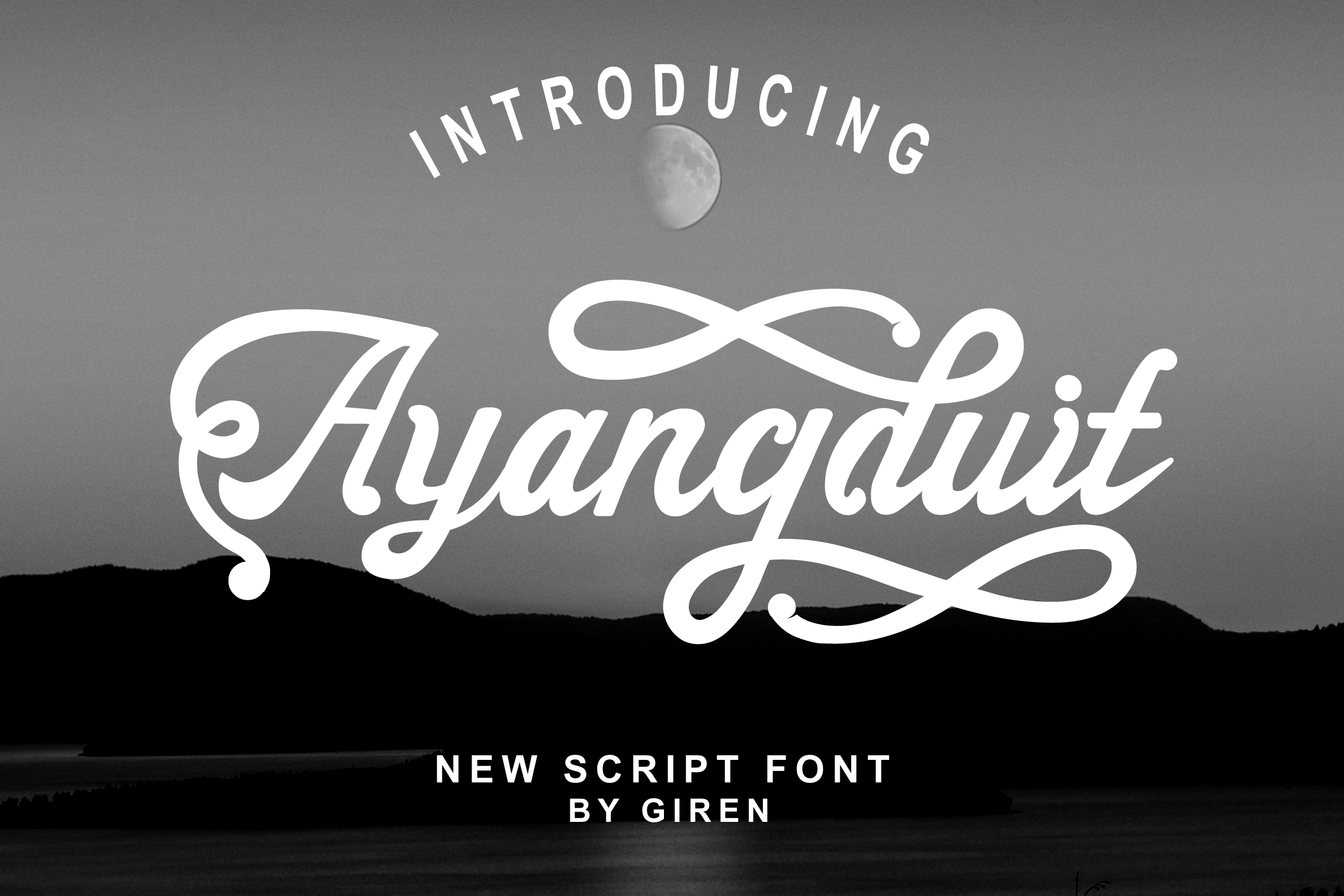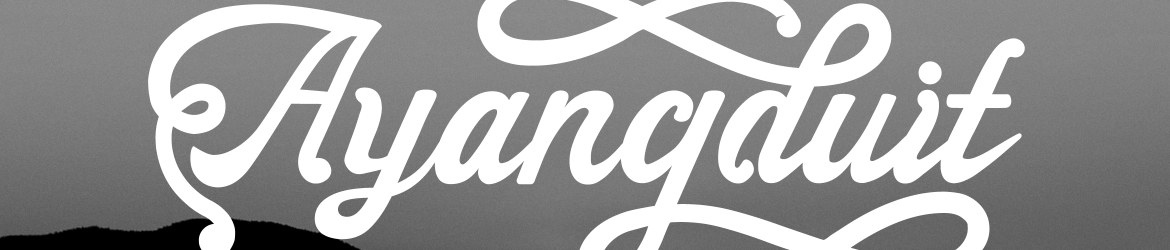
Ayangduit Script Font – Download Grátis
Olá a todos! Estamos felizes por anunciarmos a nova fonte chamada “Ayangduit”. Esta fonte é perfeitamente adequada para uma variedade de projetos, incluindo logomarcas, roupas, mensagens, cartões de visita, outdoors, marcas d’água, assinaturas, revistas e websites, entre outros. Com um toque natural, “Ayangduit” é a escolha perfeita para você. Designada pelo designer blackkido, esta fonte é ideal tanto para aplicação digital quanto em projetos manuais. Seja em sua versão lírica ou minúscula, “Ayangduit” oferece um toque natural que se adequa à maioria dos estilos de design. Sem dúvidas, você encontrará esta fonte perfeita para complementar seus próximos projetos criativos!